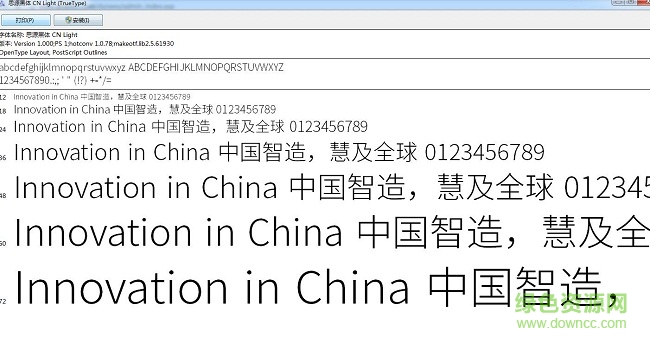
思源黑體cn light
字體sourcehansanscn-light-gbpc-euc-h是一款ttf格式的高質(zhì)量黑體字體,這款黑體的線(xiàn)條比較纖細(xì),不僅適合平面設(shè)計(jì)、網(wǎng)頁(yè)設(shè)計(jì)等領(lǐng)域,也可以適當(dāng)用在排版中,需要的小伙伴快來(lái)下載吧!
黑體字體介紹
無(wú)襯線(xiàn)體因其筆端方直被認(rèn)為是印刷黑體字形的來(lái)源,但是類(lèi)似特征在中國(guó)書(shū)法及民間用字中早已存在,如:漢代碑刻、篆刻字體及某些裝飾字體的筆端都有方直的形態(tài)。這些字體的使用從古至今未曾間斷,無(wú)疑比西文無(wú)襯線(xiàn)體更接近于黑體。
思源黑體cn light